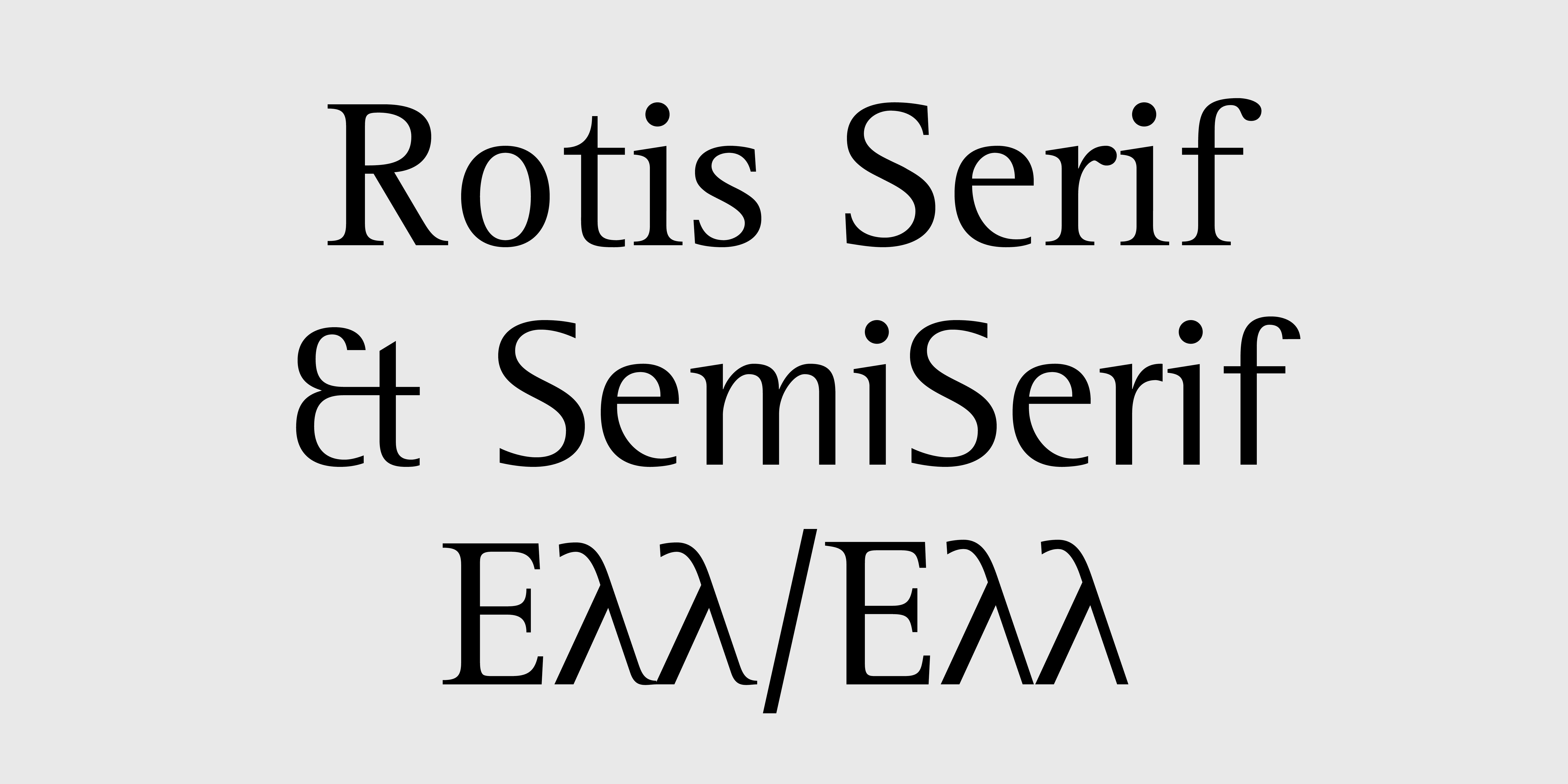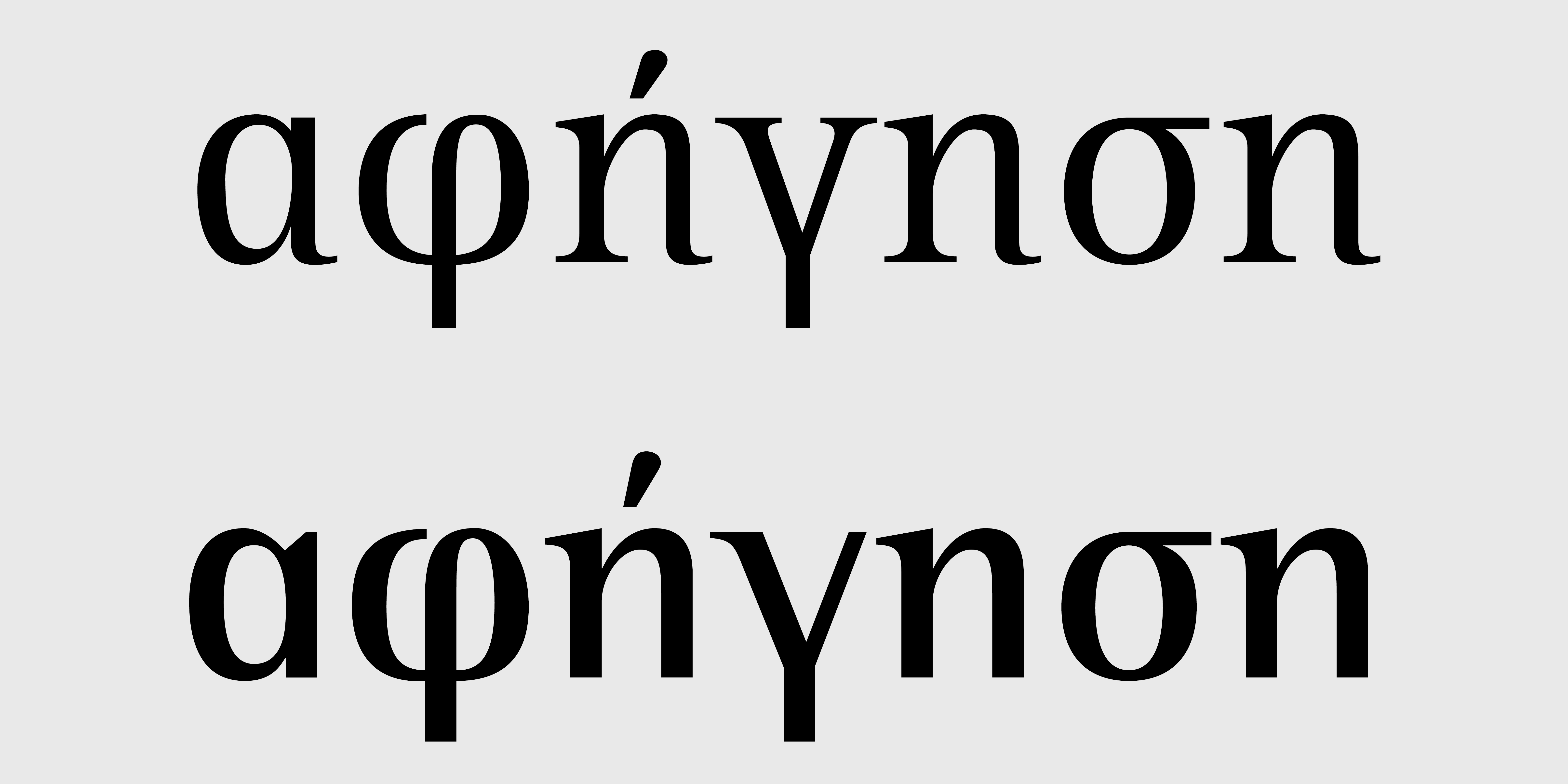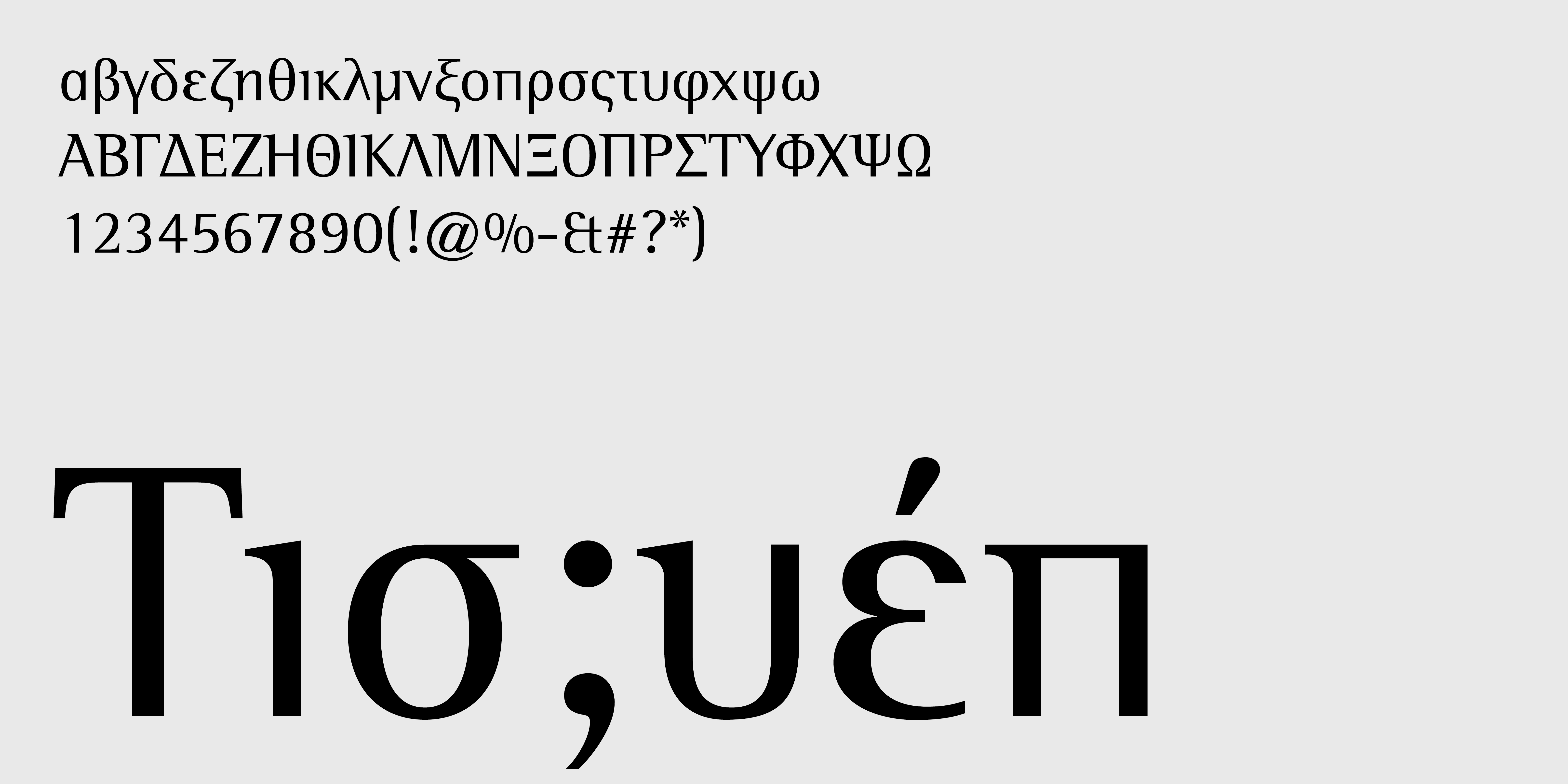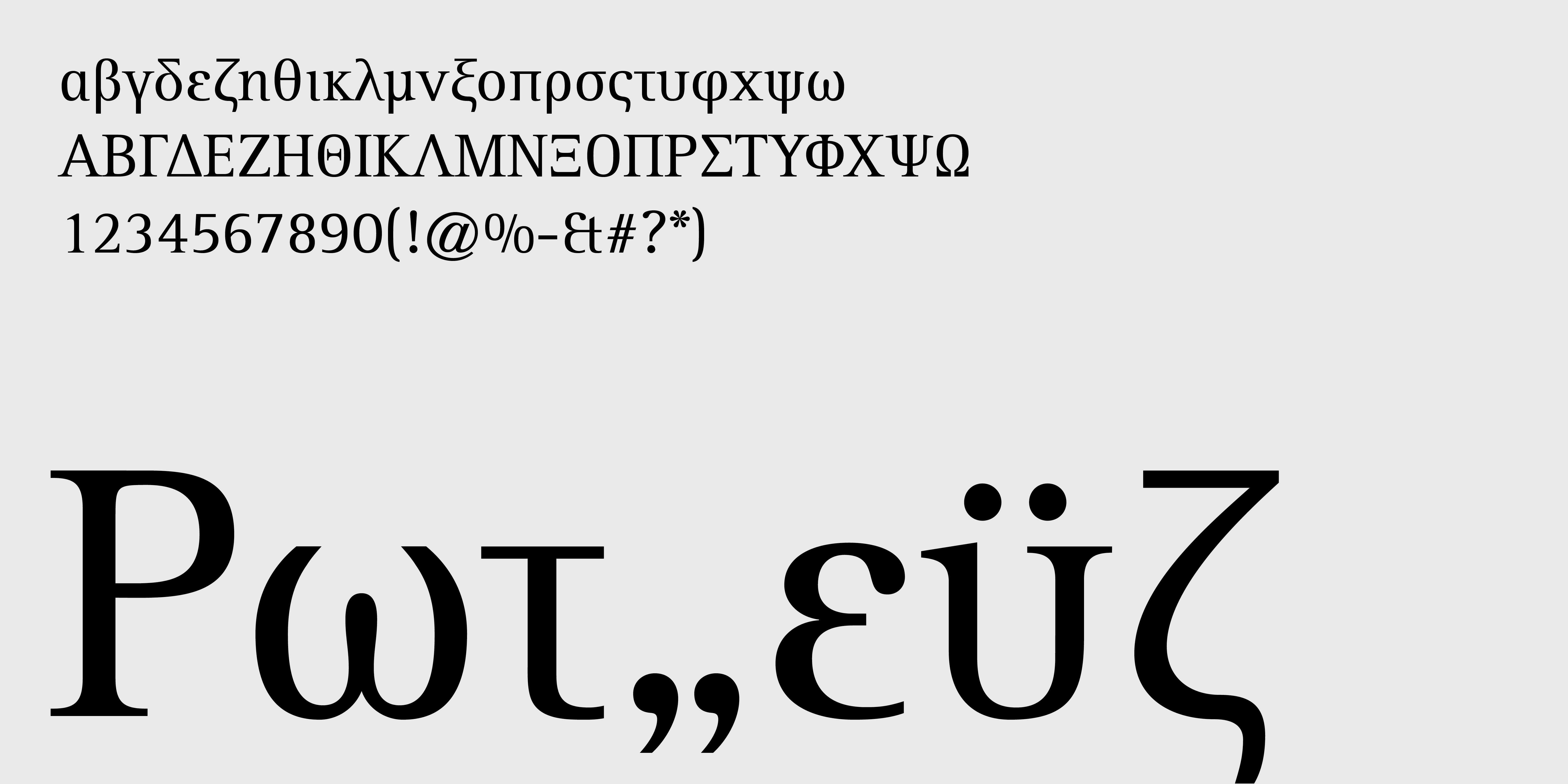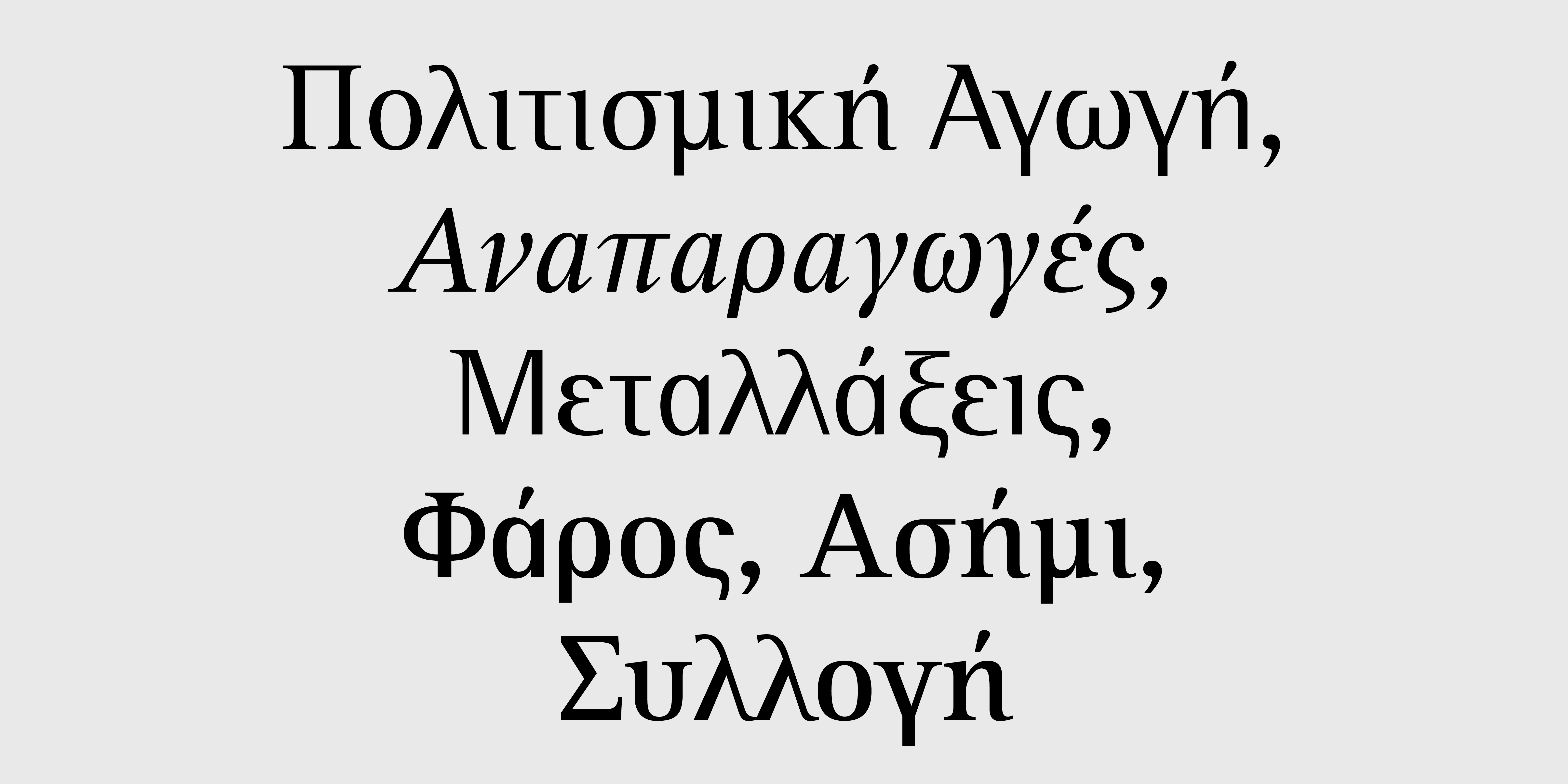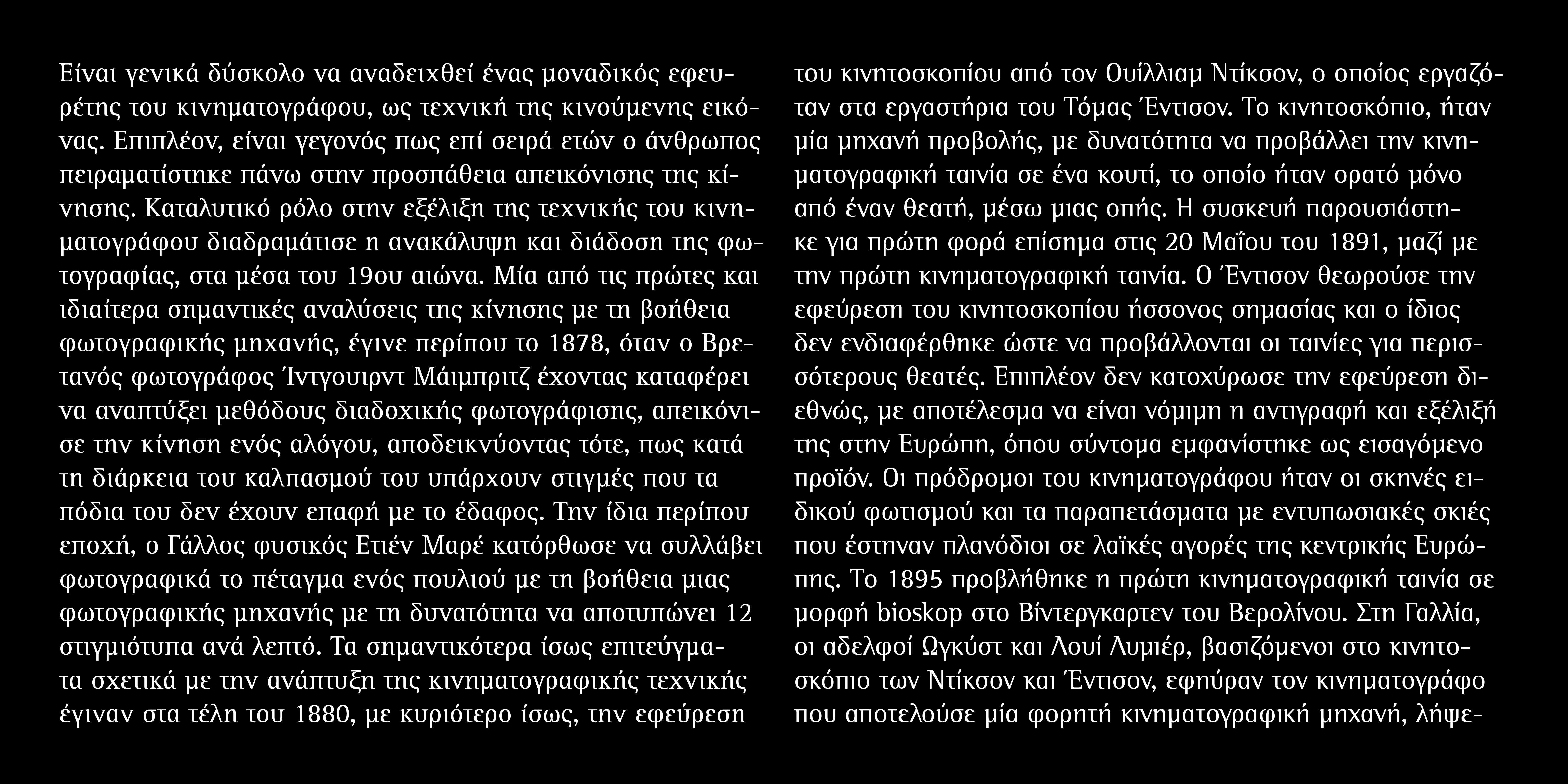
Rotis Serif & SemiSerif Ελληνικά Collection
Rotis SemiSerif Ελληνικά
Regular BoldRotis Serif Ελληνικά
Regular Italic BoldΗ οικογένεια γραμμάτων Rotis αποτελείται από τέσσερις εκδοχές, τις Sans, Serif, SemiSans και SemiSerif. Πήραν το όνομά τους από το χωριό στο Allgäu όπου ζούσε ο Otl Aicher από τον 1972. Ο στόχος του Aicher ήταν να σχεδιάσει μια οικογένεια γραμματοσειρών που θα μπορούσε να ανταποκριθεί σε σχεδόν οποιαδήποτε τυπογραφική ανάγκη. Η Rotis δίνει μια εντύπωση δύναμης και γενναιοδωρίας και οι τέσσερις τύποι της μπορούν να χρησιμοποιηθούν αλληλένδετα μεταξύ τους.